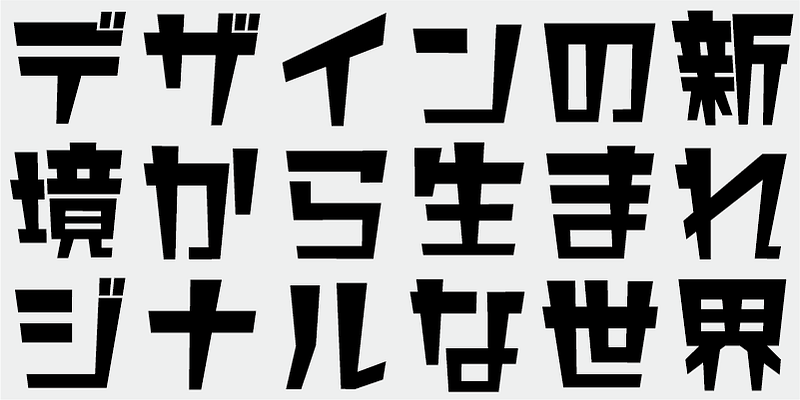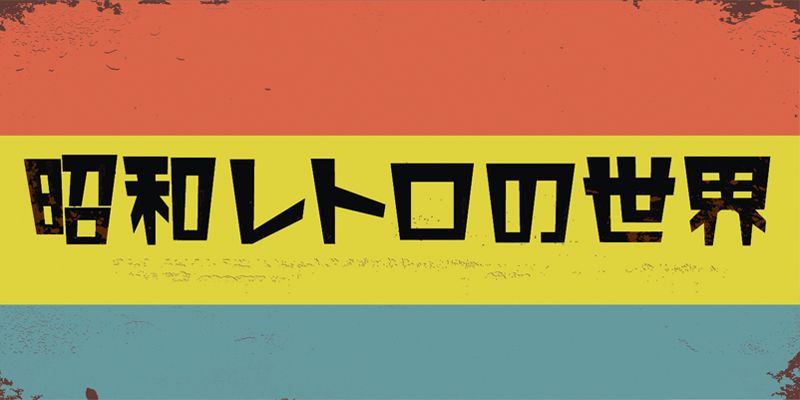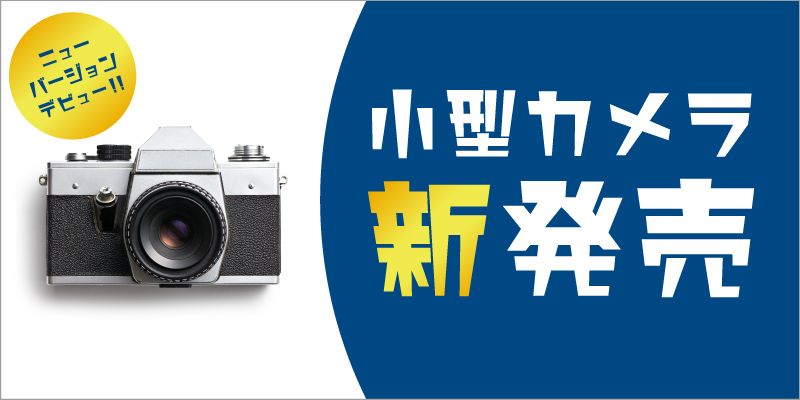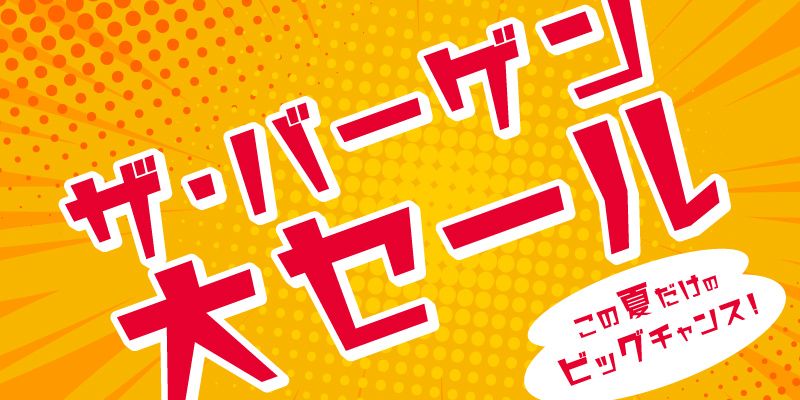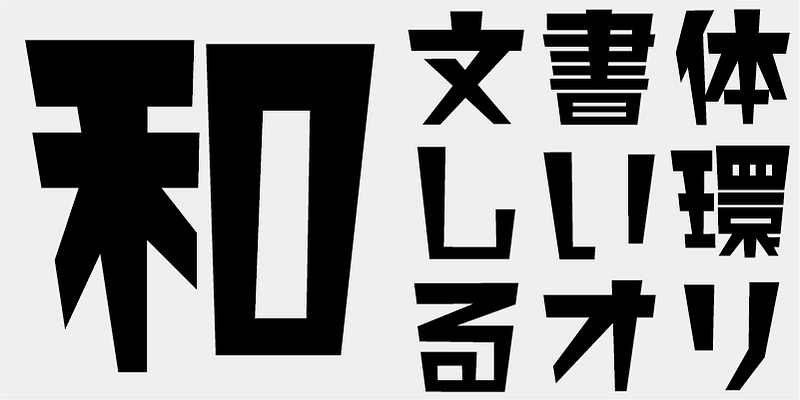
Futuristische und zugleich nostalgische und komische Merkmale sind für diese Schriftart typisch.
Sie hat die warme und aktive Atmosphäre, die man aus alten Comics kennt. Die Perspektive der Jugend – die sich eine strahlende Zukunft vorstellt – ist in das Design integriert.
Diese Display-Schrift sollte für Titel und Zeilen in größeren Formaten verwendet werden.
Mit dieser Schrift können Sie einen Hauch von Nostalgie und warmherziger Verspieltheit vermitteln.
Diese Schrift enthält die 1.000 wichtigsten Kanji-Zeichen, die aus den Häufigkeitstabellen von Zeitungsunternehmen, Verlagen und Sprachforschungsinstituten ausgewählt wurden, sowie 206 Kana-Zeichen und Satzzeichen.